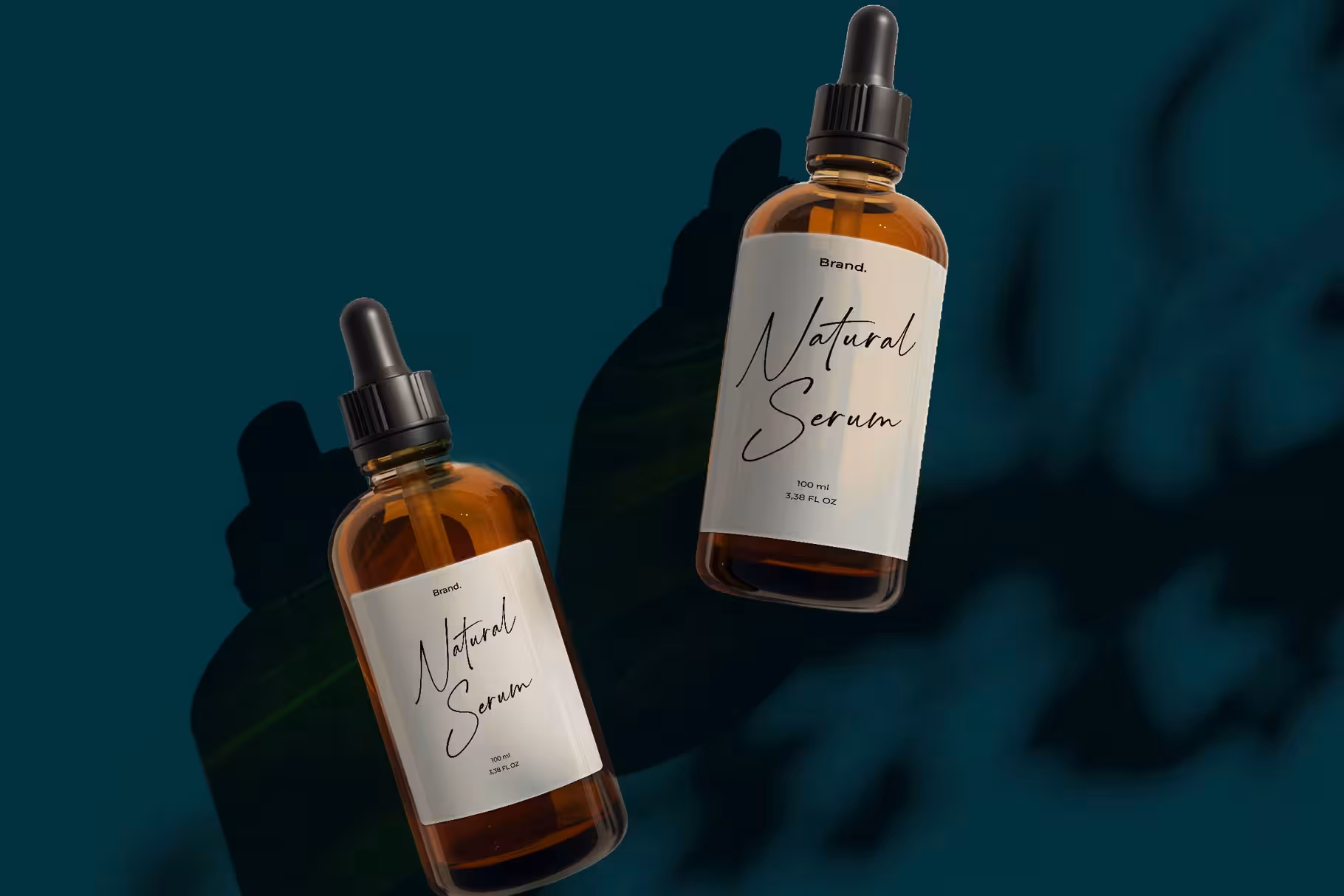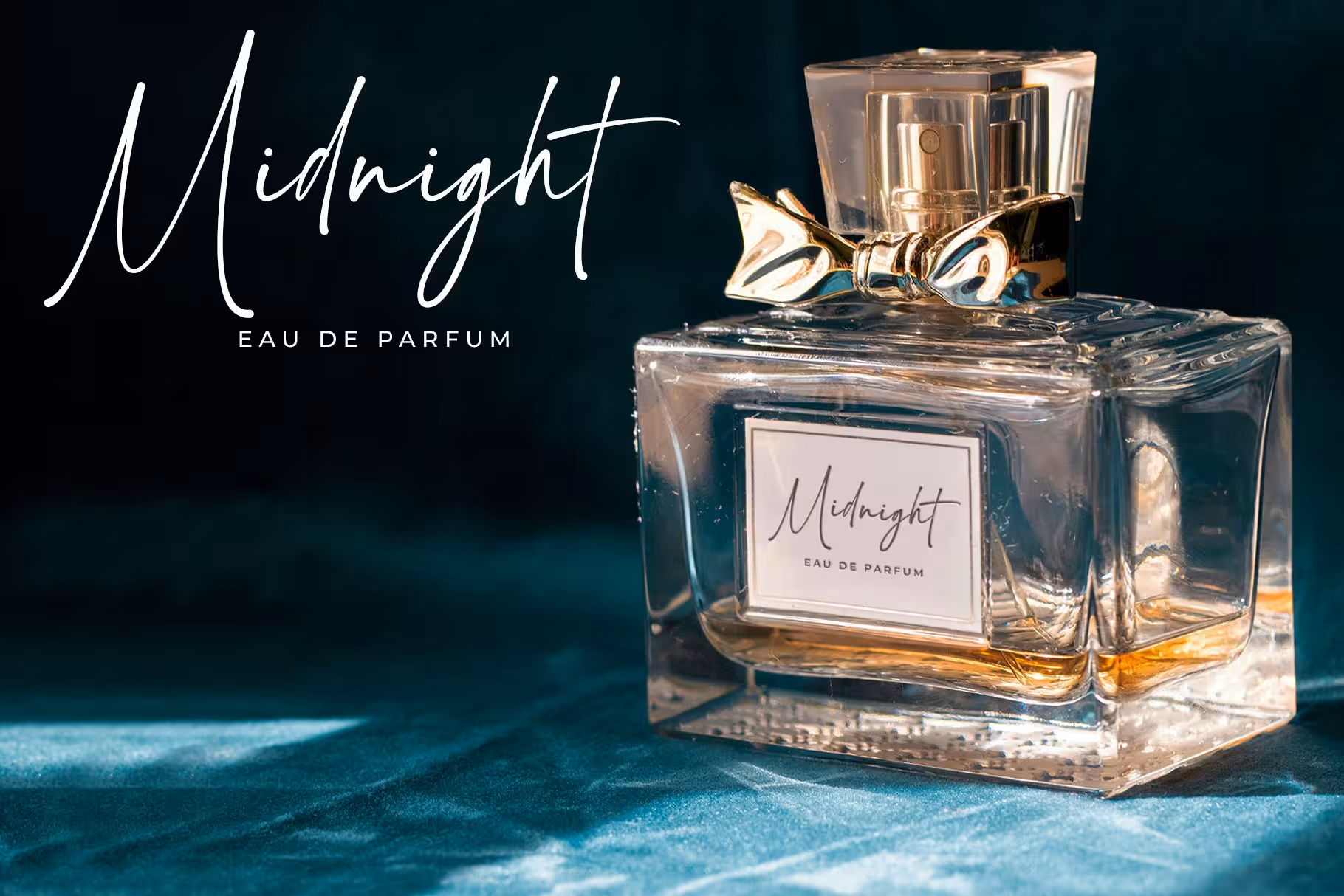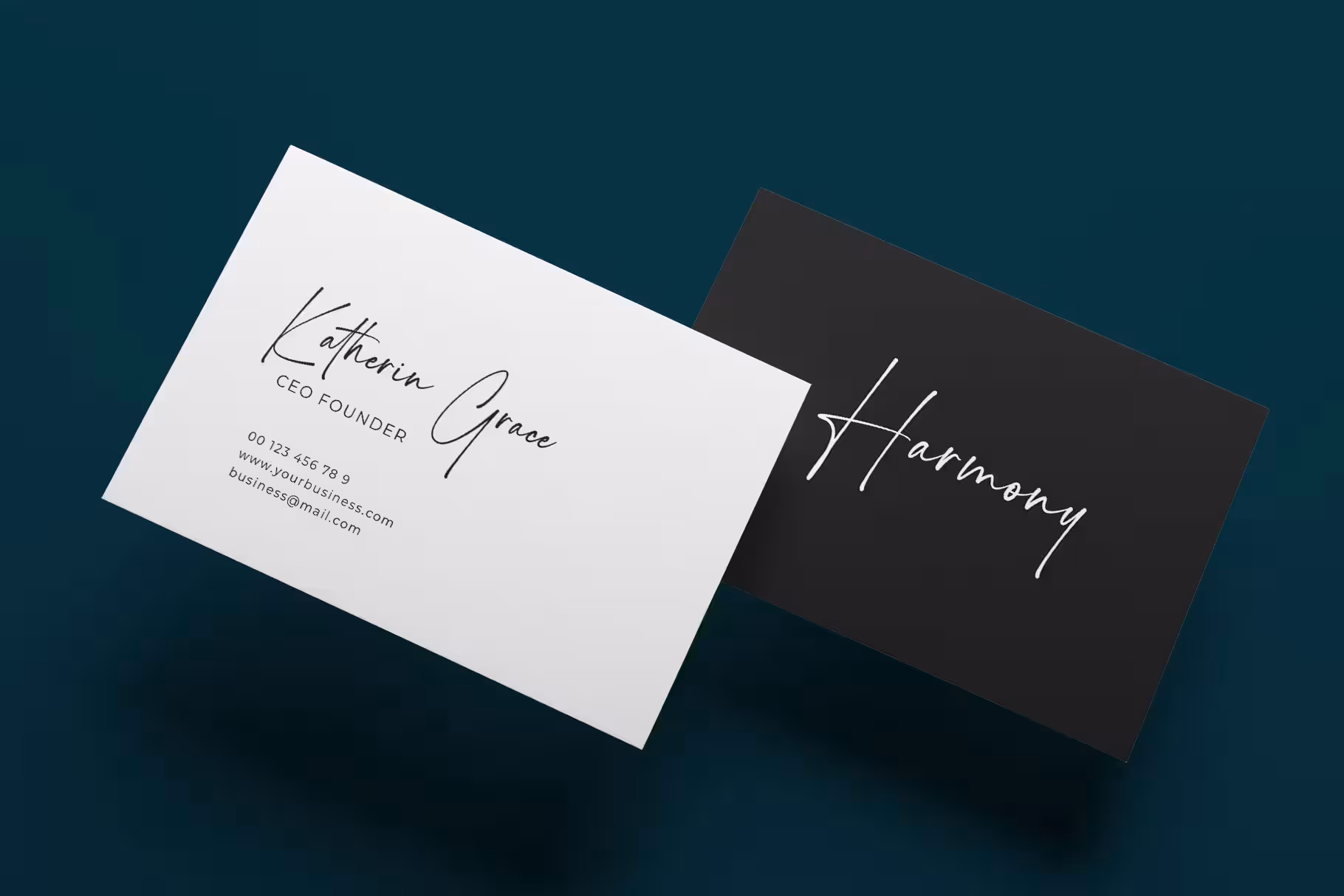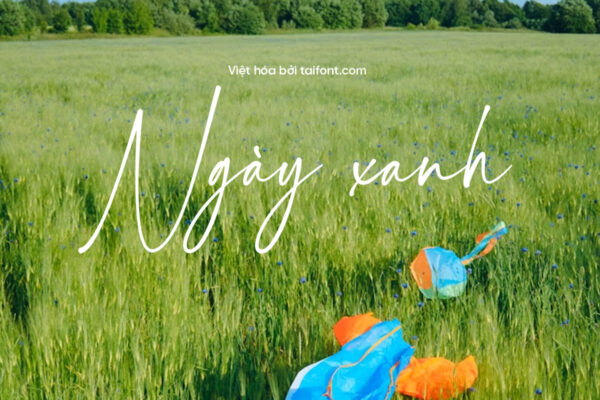
Giới thiệu về Font TF Gettisay Việt hóa
TF Gettisay Việt hóa là một font chữ viết tay (script font) nổi bật với vẻ đẹp tinh tế, lãng mạn và đầy duyên dáng, lý tưởng để tạo nên sự sang trọng và cá tính riêng cho các thiết kế. Font này mang đến cảm giác như một bức thư pháp được viết tay một cách mềm mại và uyển chuyển, toát lên sự nghệ thuật và đẳng cấp.
Với sự duyên dáng trong từng đường nét và tính thẩm mỹ cao, Gettisay là lựa chọn hoàn hảo cho các ấn phẩm cần sự sang trọng và khác biệt, đặc biệt là trong các lĩnh vực:
- Thiết kế nước hoa và mỹ phẩm: Hoàn hảo để sử dụng trên bao bì sản phẩm, nhãn chai, hoặc các chiến dịch quảng bá. Font này giúp khẳng định chất lượng, sự sang trọng và vẻ đẹp tinh túy của sản phẩm, thu hút ánh nhìn của khách hàng và truyền tải thông điệp về sự quyến rũ, đẳng cấp một cách tinh tế.
- Thiết kế thiệp cưới: Lý tưởng để viết tên cô dâu chú rể, lời mời, hoặc các thông tin chi tiết trên thiệp cưới, menu tiệc, bảng tên khách mời. Những nét chữ mềm mại, uyển chuyển sẽ biến mỗi tấm thiệp thành một tác phẩm nghệ thuật, mang đậm dấu ấn cá nhân và sự lãng mạn của ngày trọng đại, đồng thời truyền tải sự ấm áp và trang trọng.
- Thiết kế thời trang: Phù hợp cho các thương hiệu thời trang cao cấp, từ logo, nhãn mác sản phẩm, lookbook, đến các chiến dịch quảng bá bộ sưu tập. Font này giúp truyền tải vẻ đẹp thanh lịch, đẳng cấp và độc đáo của trang phục, nâng tầm giá trị thương hiệu.
- Thiết kế sự kiện và ấn phẩm hạng sang: Tuyệt vời cho các thiệp mời sự kiện VIP, hoặc các tài liệu quảng cáo cần tạo ấn tượng về sự độc quyền và đẳng cấp.
Với TF Gettisay Việt hóa, bạn có thể dễ dàng thổi hồn lãng mạn, sự tinh tế và vẻ đẹp vượt thời gian vào các thiết kế, tạo ra những sản phẩm không chỉ đẹp mắt mà còn đầy cảm xúc và sức hút đặc biệt.
Font Việt hóa TF Gettisay